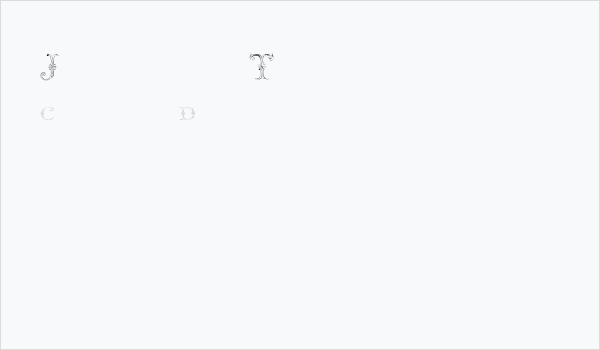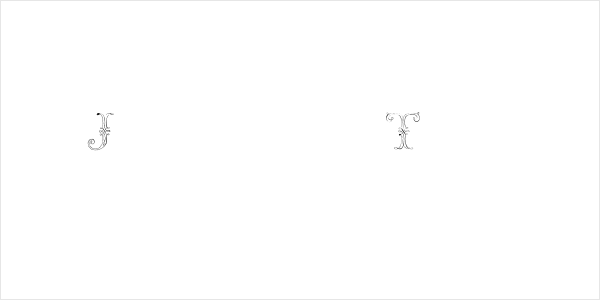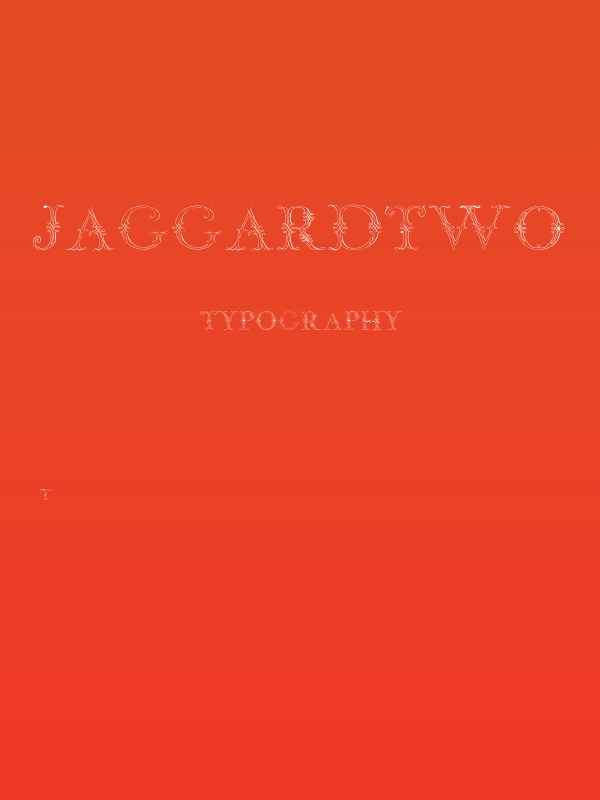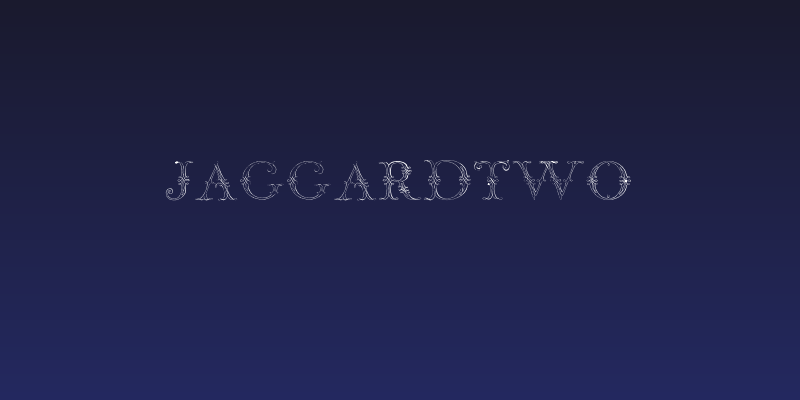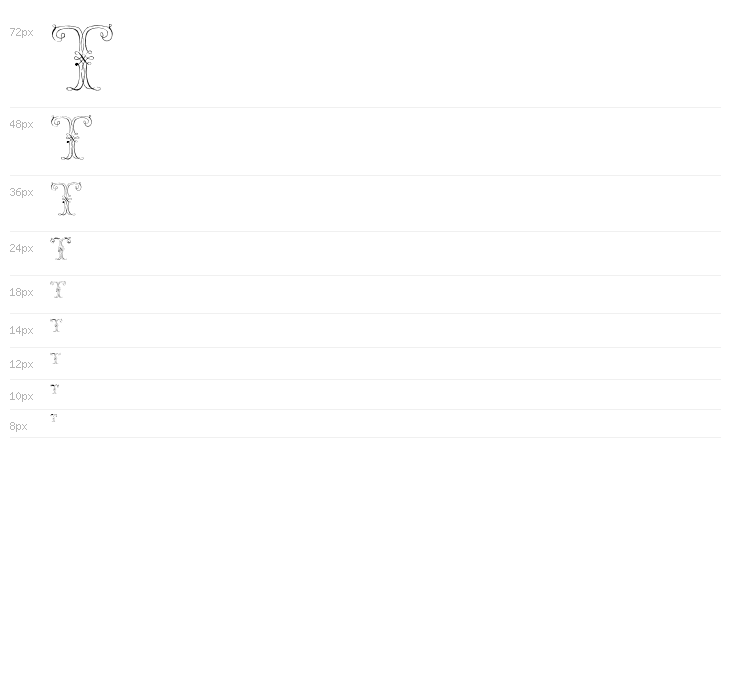
JaggardTwo Font
✎ Calligraphic
| Gesamtstil | Vintage |
| Vorgeschlagene Projekte | Ideal for wedding invitations, vintage-themed posters, book covers, and branding that requires a classic and sophisticated look. |